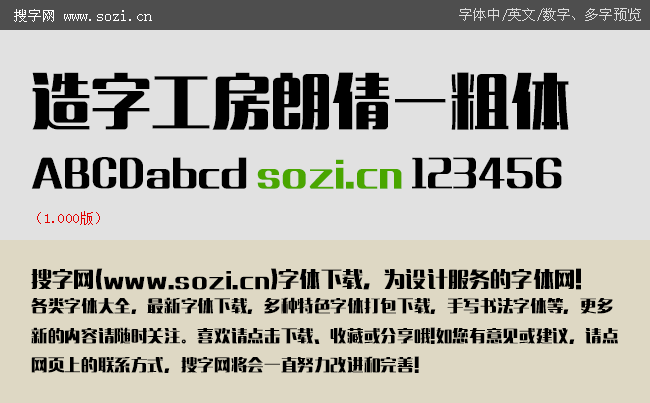
造字工房朗倩粗體(MFLangQian_Noncommercial-Bold)
搜字網提供一款造字工房朗倩粗體中文藝術字體下載,造字工房朗倩體共三款,筆畫簡潔、粗細分明,中正不失圓潤,曲線流暢,結構穩重大方,整套字形柔和飽滿,如玉似珠,為漢字灌注了無限生機。整體字形姿態橫生,結構疏朗飄逸,字里行間蘊藏一種閑適沉靜之美。適合畫冊設計,海報設計,包裝設計等廣告設計場合使用。